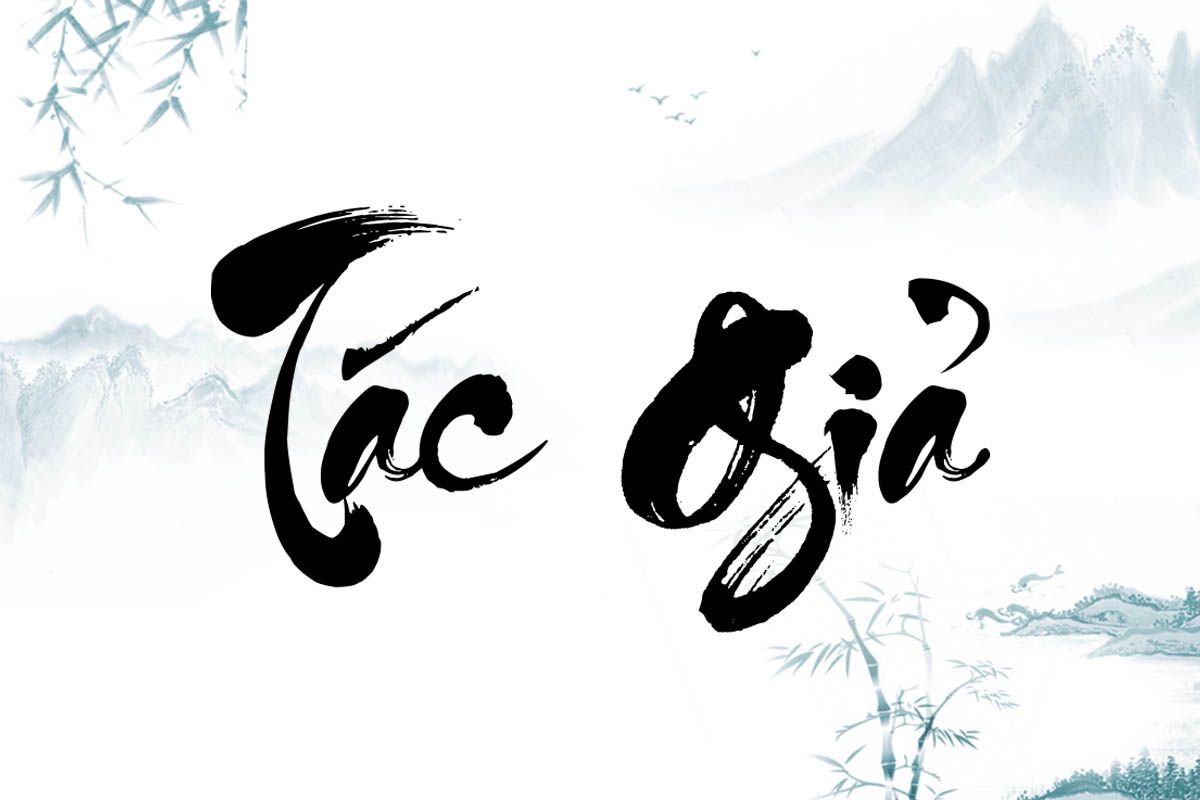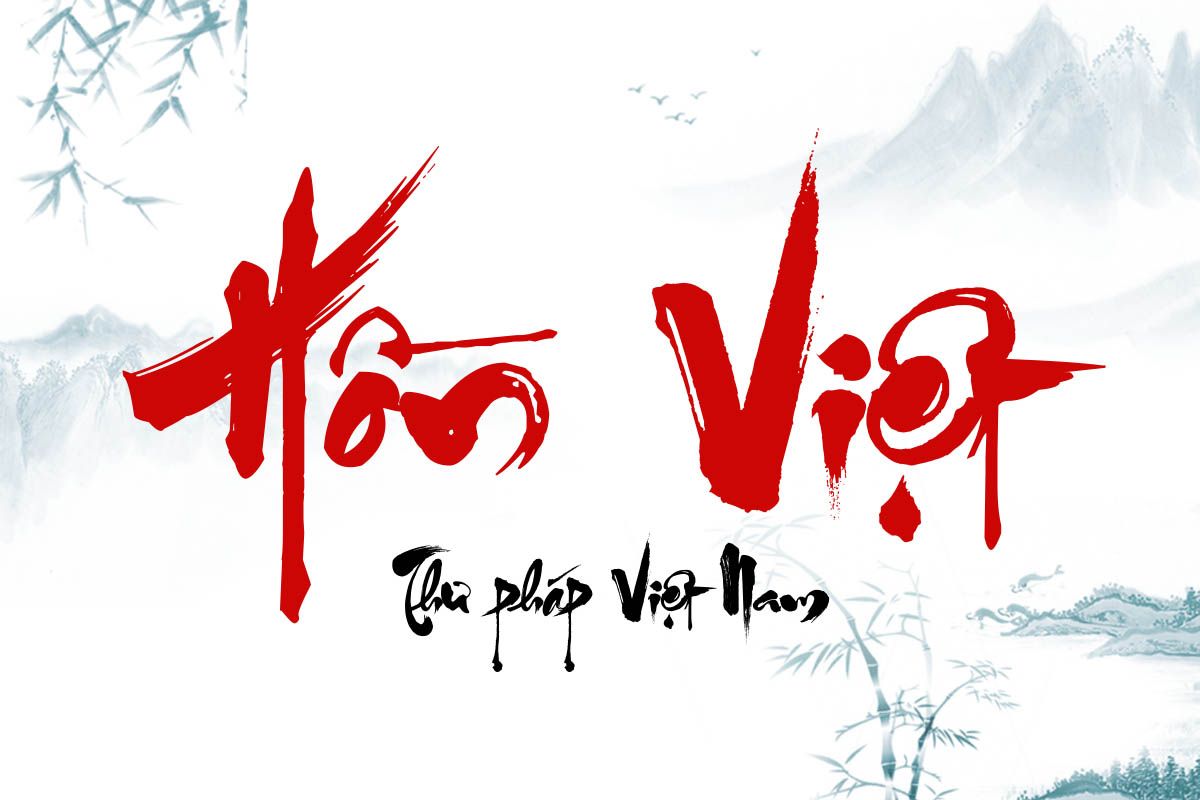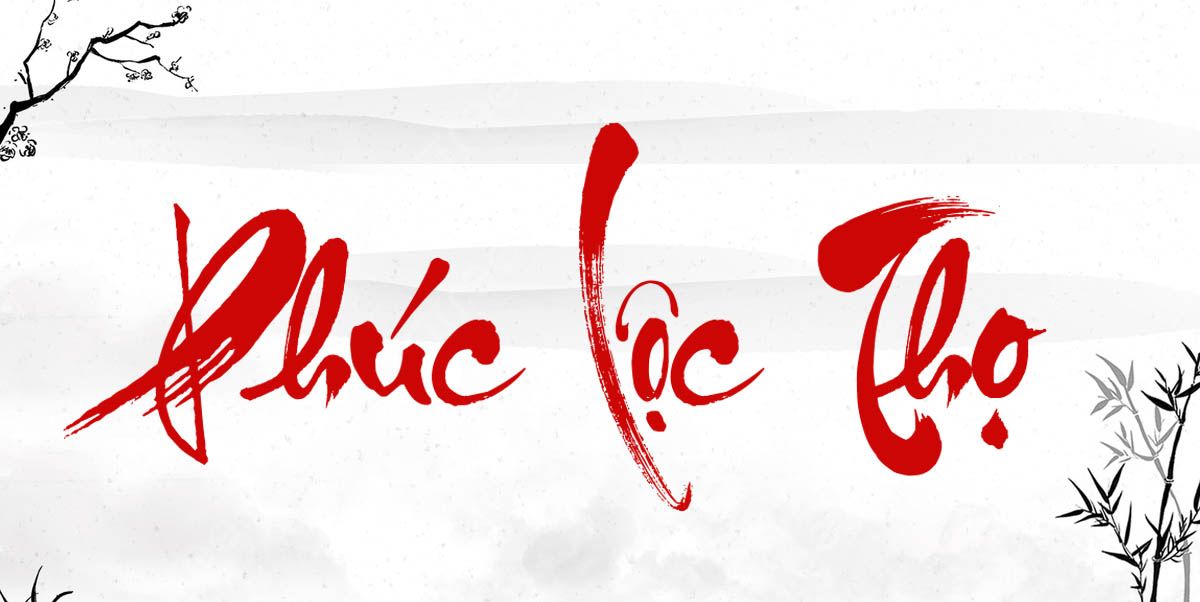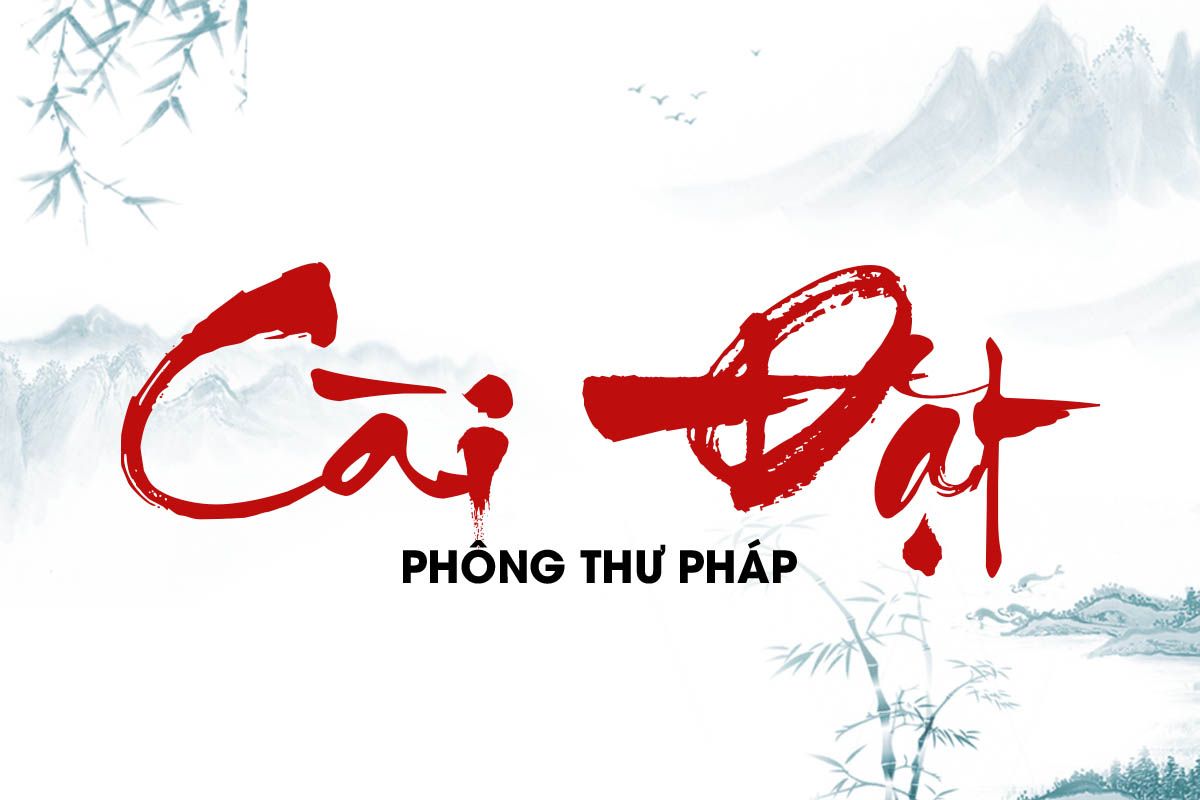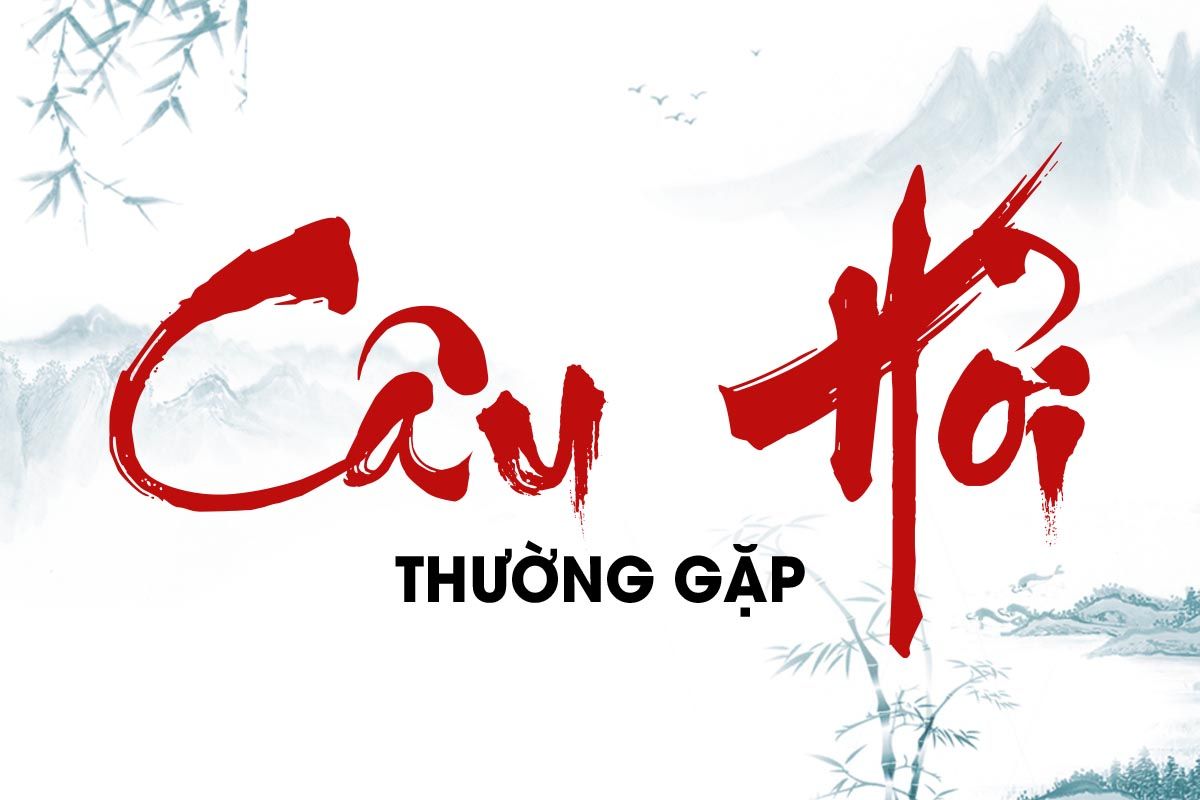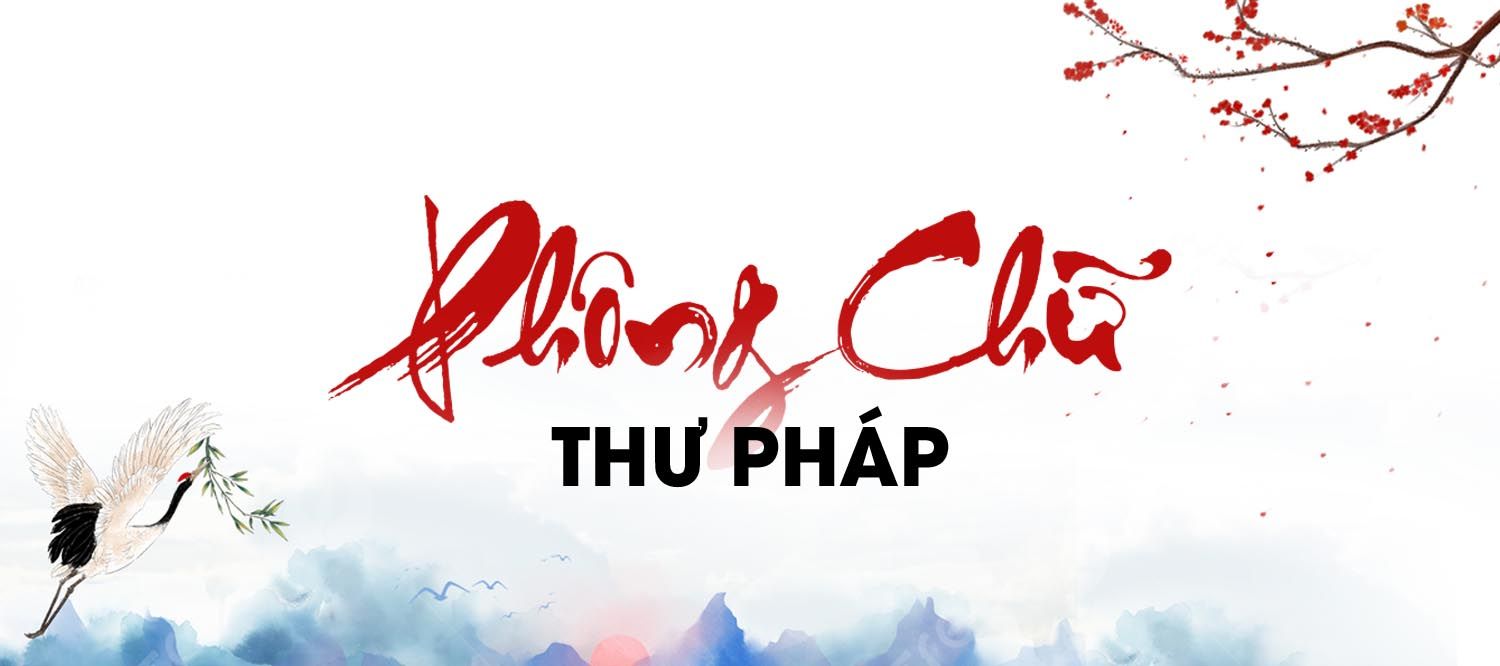
UTM Thư Pháp Thiên Ân là một trong những bộ font thư pháp Việt hóa nổi bật, mang đậm hơi thở truyền thống và bản sắc văn hóa phương Đông. Với đường nét mềm mại, uyển chuyển nhưng vẫn rõ ràng và sắc nét, font này rất được ưa chuộng trong các thiết kế liên quan đến ngày Tết, các sự kiện văn hóa, thiệp mừng và tranh thư pháp.
Năm 2025, với nhu cầu thể hiện cá tính và tinh thần dân tộc trong thiết kế ngày càng tăng, UTM Thư Pháp Thiên Ân đang trở thành lựa chọn hàng đầu cho các designer, giáo viên, nghệ nhân thư pháp và người yêu thích thiết kế đồ họa Việt Nam.
Font chữ UTM Thư Pháp Thiên Ân được phát triển bởi tác giả Đinh Kiên – một nhà thiết kế font đầy tâm huyết với thư pháp Việt.
UTM Thư Pháp Thiên Ân nổi bật với các nét bút mềm mại, uyển chuyển giống như những nét viết bằng cọ thư pháp trên giấy dó. Chữ cái có phần chân dài, đuôi vút nhẹ, tạo nên cảm giác thanh thoát nhưng vẫn giữ được sự vững chãi và chỉn chu trong tổng thể.
Font sử dụng đối lập giữa các nét đậm và mảnh để tạo chiều sâu, đặc biệt hiệu quả khi dùng trên nền đơn sắc hoặc phối cùng các họa tiết truyền thống như hoa sen, trống đồng. Sự cân bằng giữa tính thẩm mỹ và khả năng đọc giúp font này không chỉ đẹp mà còn dễ sử dụng trong nhiều ngữ cảnh khác nhau.
Font UTM Thư Pháp Thiên Ân mang lại cảm giác trang trọng khi dùng trong thiệp Tết với các chữ “Phúc”, “Lộc”, “Thọ” – phù hợp để gửi gắm lời chúc may mắn, viên mãn đầu xuân.
Trong thiết kế poster lễ hội, font này kết hợp hài hòa với nền đỏ, vàng cùng hình ảnh bánh chưng, pháo hoa, tạo nên không khí rực rỡ và đậm chất truyền thống.
Khi ứng dụng vào tranh treo tường, những từ như “Thiên Ân” được thể hiện bằng font này tạo cảm giác cổ kính, trang nghiêm – thích hợp cho không gian nội thất mang hơi hướng văn hóa.
Với bao lì xì handmade, font chữ giúp tăng tính dân gian và thủ công, tạo nên sản phẩm vừa tinh tế vừa gần gũi.
Font thư pháp mô phỏng cách viết bằng cọ, nét kéo dài, có tính mỹ thuật cao hơn.
8. Kết nối chủ đề: Vẻ đẹp truyền thống & thiết kế hiện đại
UTM Thư Pháp Thiên Ân là minh chứng cho việc kết hợp thành công giữa nghệ thuật thư pháp cổ điển và thiết kế hiện đại. Dù bạn là người thiết kế chuyên nghiệp hay đơn giản chỉ là người yêu cái đẹp Việt, font này sẽ giúp bạn thổi hồn vào từng sản phẩm.